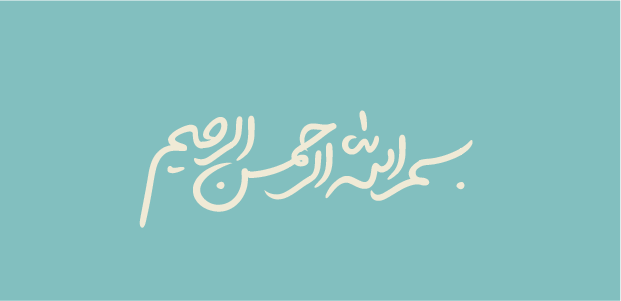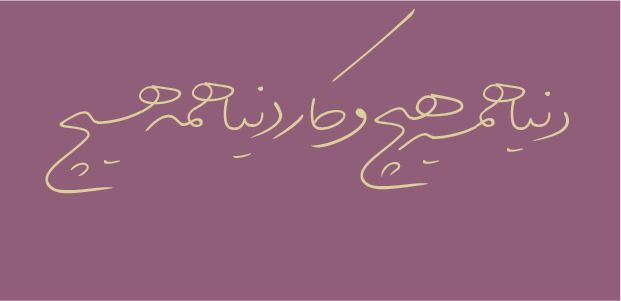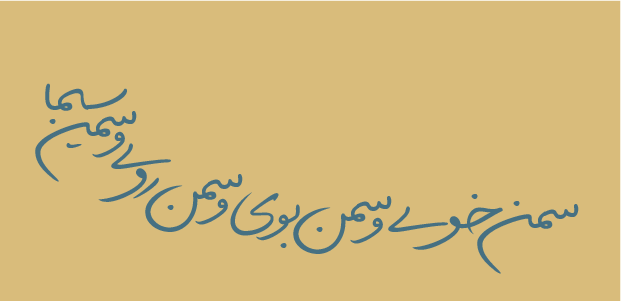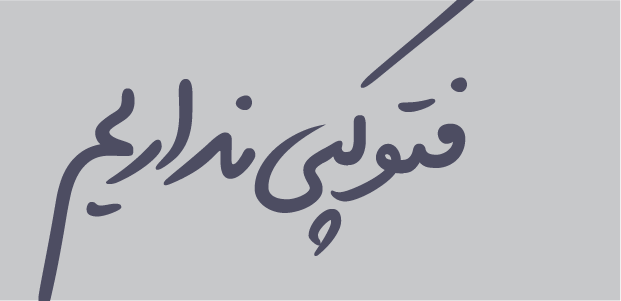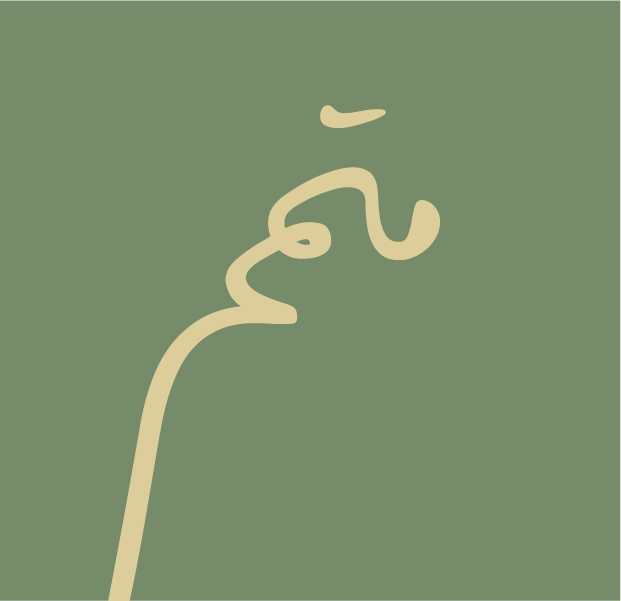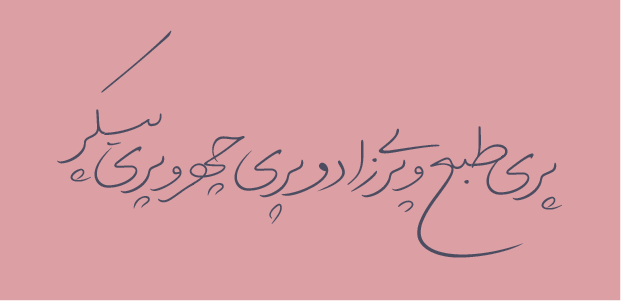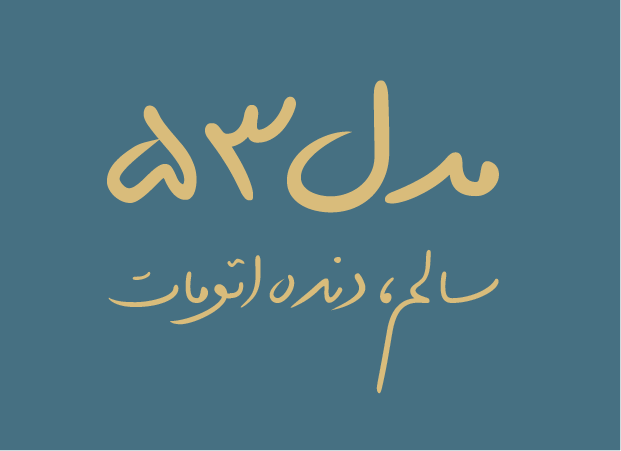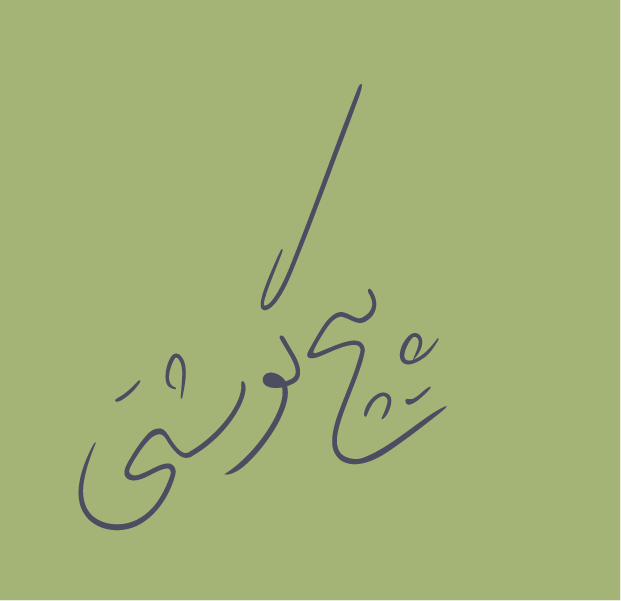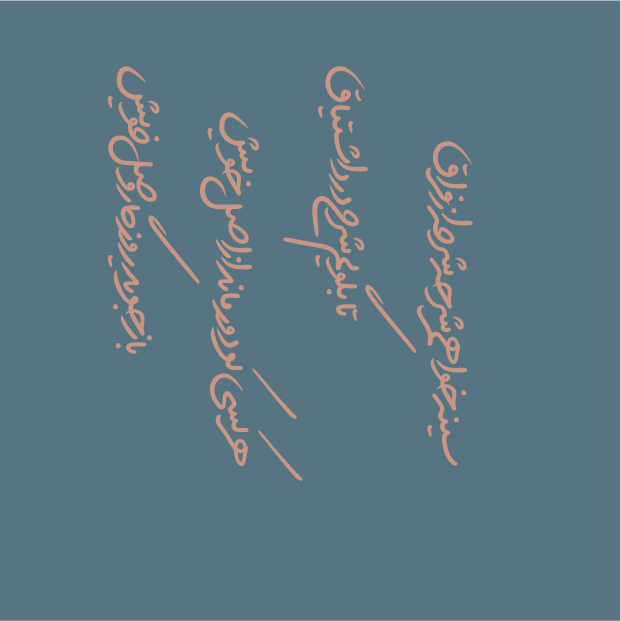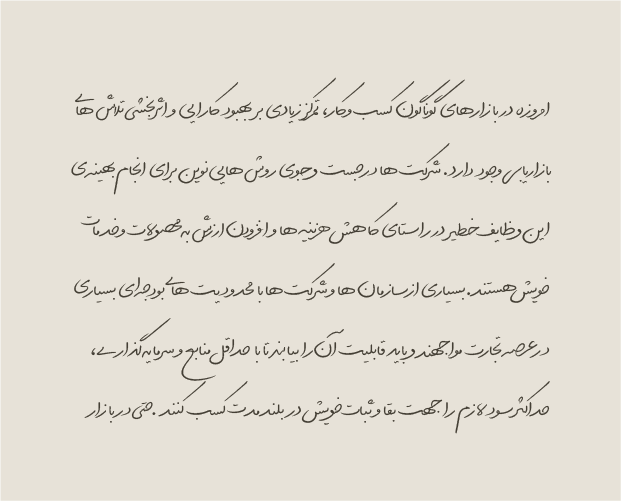
درباره قلم لیلا
خانوادهی قلم (فونت) لیلا بر پایهی دستخط خواهرم طراحی شد و من تلاش کردم تا با بررسی و الگوبرداری از جزوهها و نوشتههایش، حرکت سریع دست، تغییرات ضخامت خط و حرکتهای خودکار را بازنمایی کنم تا نوشته مصنوعی بهنظر نرسد. همچنین امکان استفاده از مرکبات و حروف جایگزین متنوع باعث جلوگیری از تکرار زیاد فرمها میشود و حس بداهگی نوشتن را القا میکند. طراحی لیلا سال ۱۳۸۷ آغاز شد و وزن Regular آن در سال ۱۳۹۳ پایان یافت، لیلای Light و Bold در سال ۹۵ طراحی و اجرا شدند. در سال ۹۹ سه وزن Thin، Extra Bold و Black به خانوادهی این قلم اضافه شد.